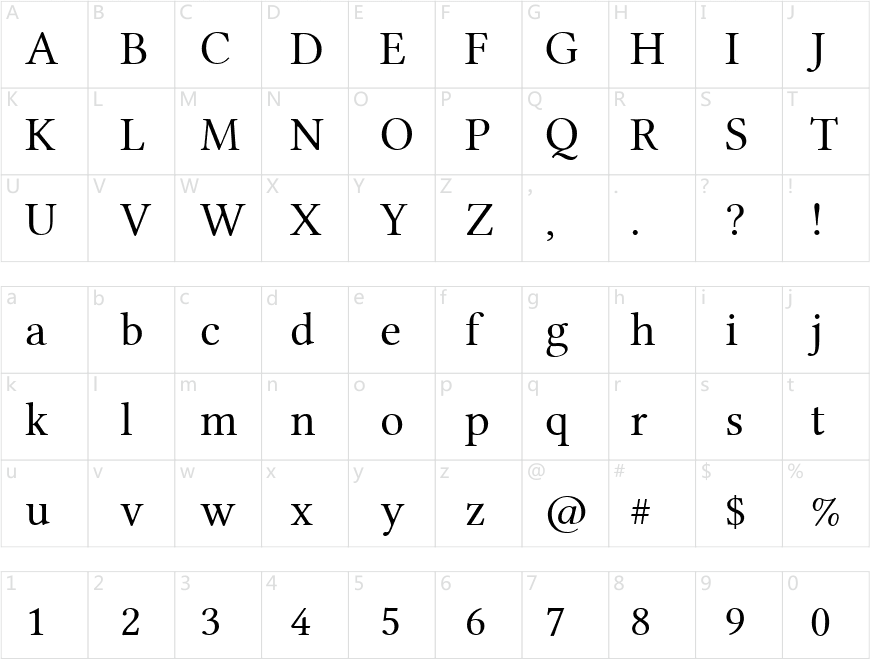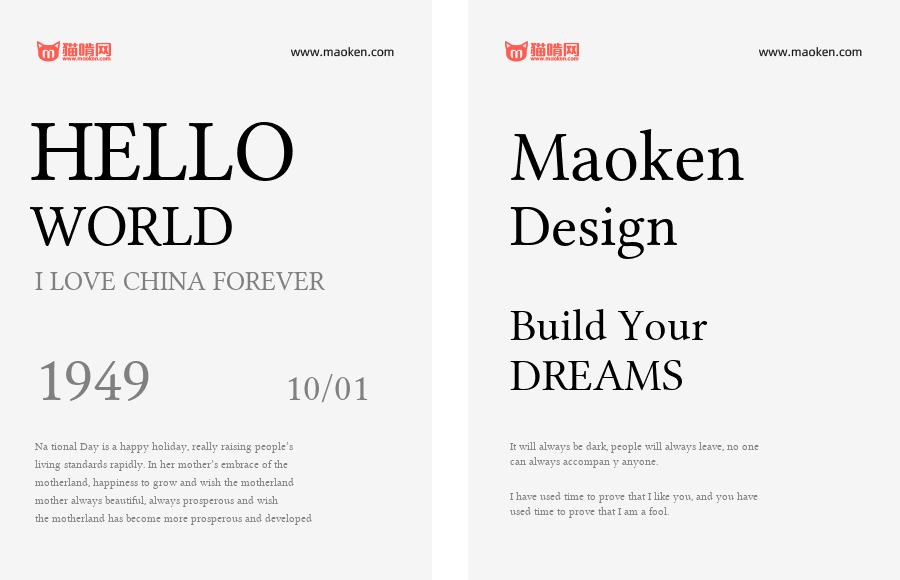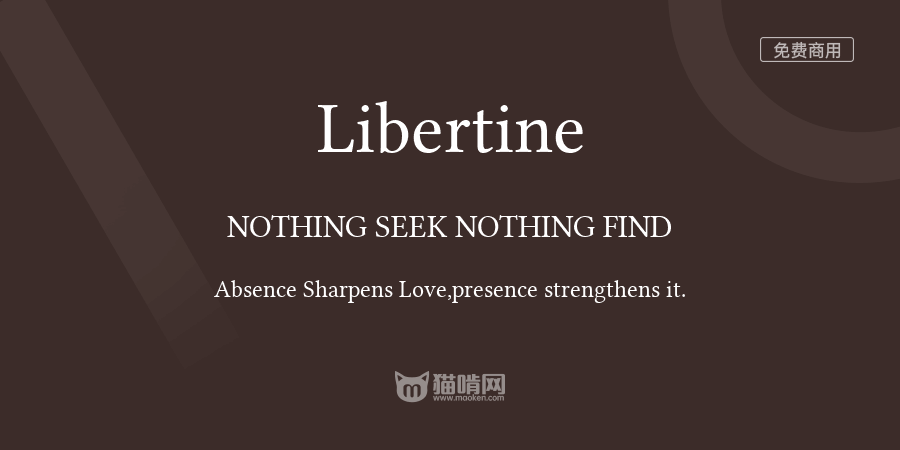
字体介绍
我们致力于开发一种多功能字体系列。它旨在为您提供类似于“Times New Roman”字体的替代选择。我们正在开发免费软件,并根据GPL和OFL的条款发布我们的字体。请查看有关许可证的段落。
我们的目标是支持许多西方语言并提供许多特殊字符。我们的字体涵盖了西方拉丁字母、希腊字母、西里尔字母(以及它们的特定增强功能)、希伯来语、国际音标等编码页面。此外,该字体还实现了连字、小型大写字母、不同的数字样式、科学符号等排版特性。Linux Libertine字体系列因此包含了超过2000个字符。在这么多的字形中,可能仍然存在一些小错误,我们希望您能向我们报告,以改进Libertine字体系列。如果您希望添加新功能,您也可以给我们写信(详情请参阅“贡献”部分)。